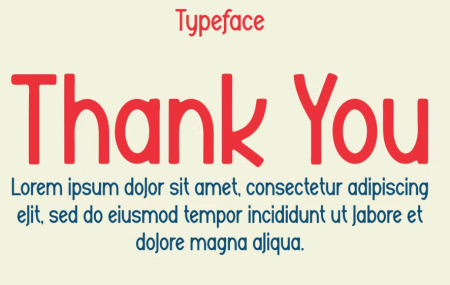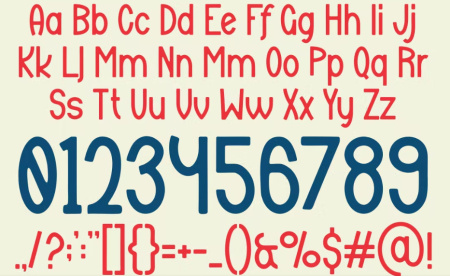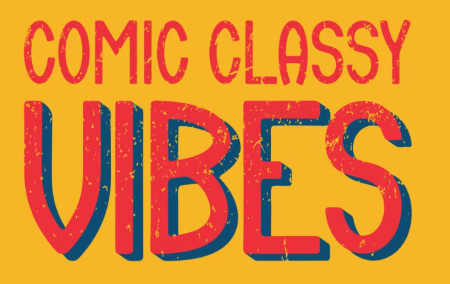
فونت مدرن انگلیسی Andak
فونت مدرن انگلیسی Andak از جی اف ایکس دانلود. این فونت مدرن یک فونت نمایشگر برجسته و زیبا است. این فونت برای هر پروژه برندسازی مانند لوگو، چاپ تی شرت و بسیاری موارد دیگر مناسب است.
✅ نام فونت: Andak
✅ حروف بزرگ
✅ حروف کوچک